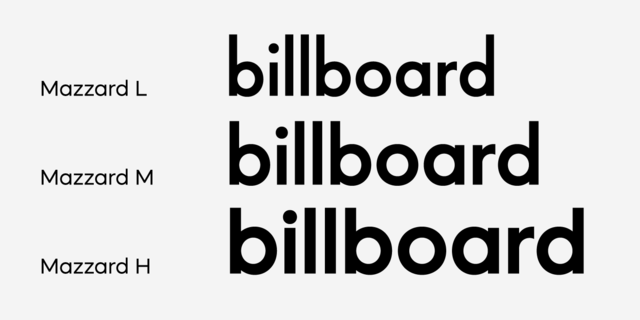
Mazzard L – часть шрифтового суперсемейства Mazzard, у этого подсемейства низкая высота строчных знаков. Суперсемейство состоит из трёх геометрических гротесков с разной высотой строчных знаков. Mazzard L имеет обширную языковую поддержку и предлагает широкий выбор альтернативных глифов. Шрифт разработал Олег Лищук в 2019 году.
Функции начертания Mazzard L MediumПрименение в макете:
Ассоциации c начертанием Mazzard L MediumКачества и характер:
урбанистический, сильный, технический, точный, ровный, убедительный, статичный, твердый, уверенный, устойчивый, искусственный, инженерный, индустриальный, техногенный, городской, резкий, четкий, острый, чертежный, урбанистичный, архитектурный, модный, чистый, позитивный, качественный, популярный, гладкий, ясный
инструмент, урбанистика, промышленность, техника, прибор, завод, чертеж, конструктор, инженер, город, дизайн, архитектура, мебель, архитектор, мода, интерьер, кафе, кино Стилистика:
Особенности семейства Mazzard LХит десятилетия: